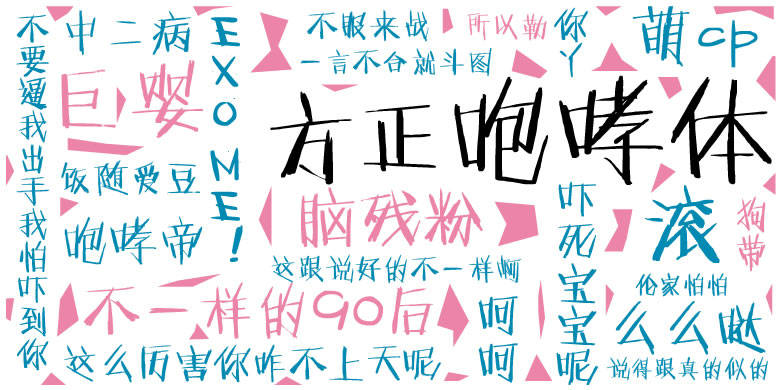
品牌:方正字库设计师:于彦舒发行时间:2013字库编码:大陆简体(GB2312-80)分类:创意书写
方正咆哮体由漫画家于彦舒创作,试图表达一种咆哮、喧嚣、争鸣的情感,排解年轻人在网络生活中的负面情绪。这款字体是在方正呐喊体的基础上,去掉浮动的方框、放大字形,好似快速涂写完成,情绪表达更加直接。方正咆哮体的风格自由奔放,适用于励志类的广告和产品包装设计,以及社交网络的个性化用字。